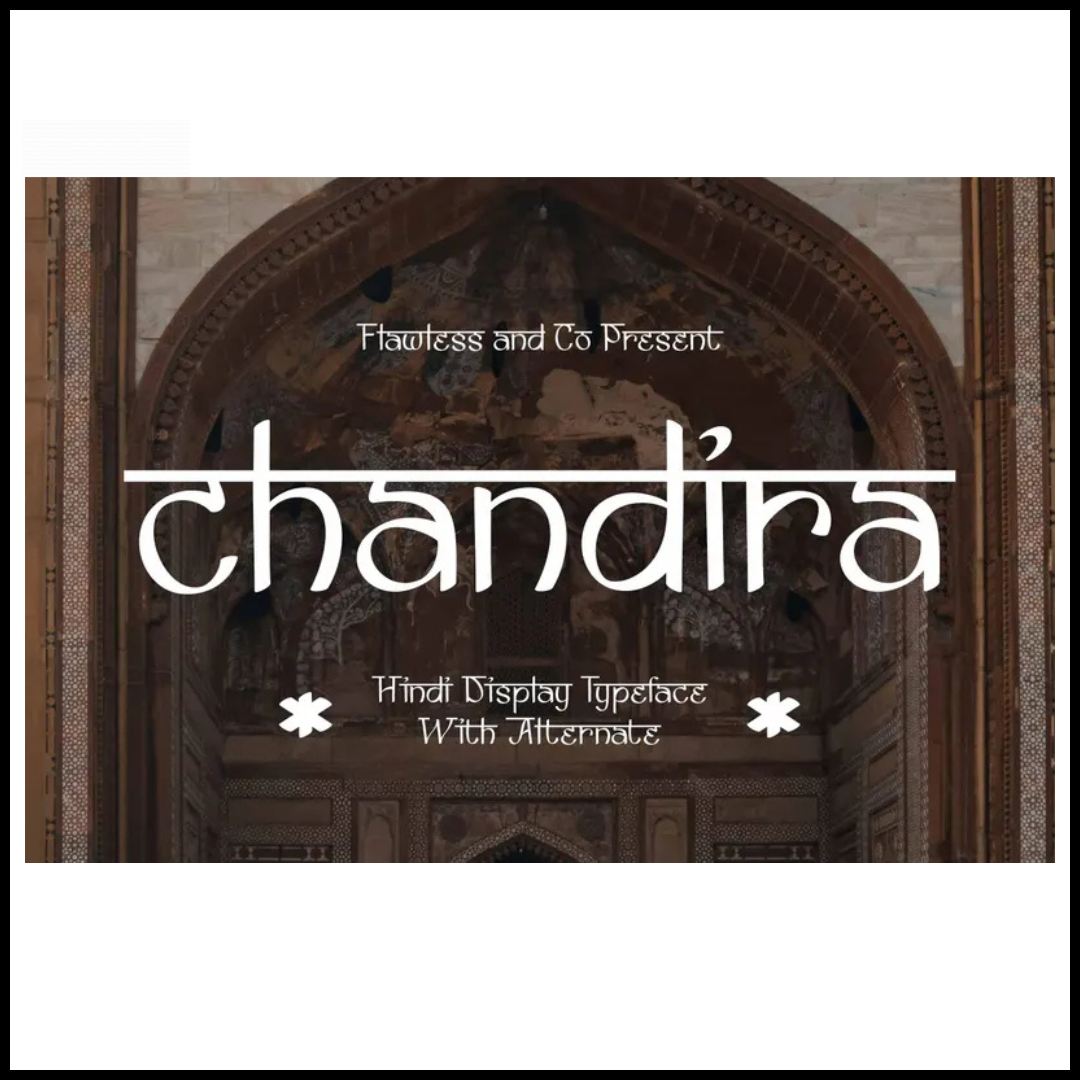
Hindi Fonts
Hindi Fonts – لمسة فنية مستوحاة من الثقافة الهندية
أضف أصالة وأناقة لمشروعاتك التصميمية مع مجموعة Hindi Fonts المصممة بعناية لتعكس روح الخطوط الهندية التقليدية مع لمسة عصرية تناسب مختلف الاستخدامات.
سواء كنت تصمم شعارات، بوسترات، دعوات، أو محتوى رقمي يحمل طابعًا ثقافيًا، فهذه المجموعة تمنحك التنوع والدقة في كل حرف. مثالية للمصممين، المبدعين، والمسوقين الباحثين عن خط يلفت الانتباه ويترك انطباعًا بصريًا قويًا.